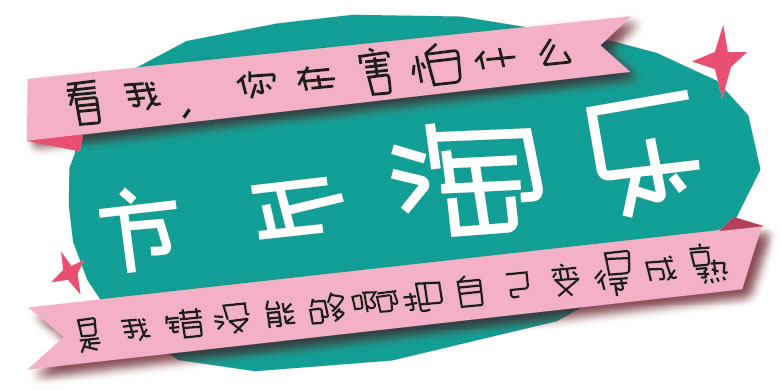
字体介绍 品牌:方正字库设计师:宋显奎发行时间:2011字库编码:大陆简体(GB2312-80)、大陆繁体(GB12345-90)分类:创意字体 英文名称:.TTF 方正淘乐由漫画家宋显奎创作。这款字体的笔画全部由等粗的直线段搭接而成,字形结构夸张,字面大小不一,字内空间充满跳跃感,部分折笔处呈圆角。方正淘乐的个性顽皮可爱,仿如一个淘气的孩童,适用于儿童类的书刊、品牌广告和产品包装设计,以及社交网络的个性化用字。 字体下载 官方下载